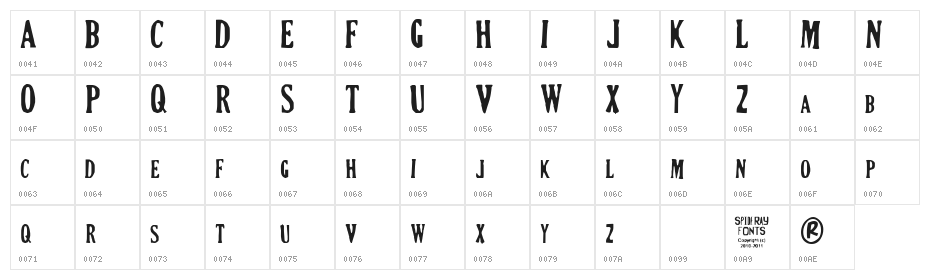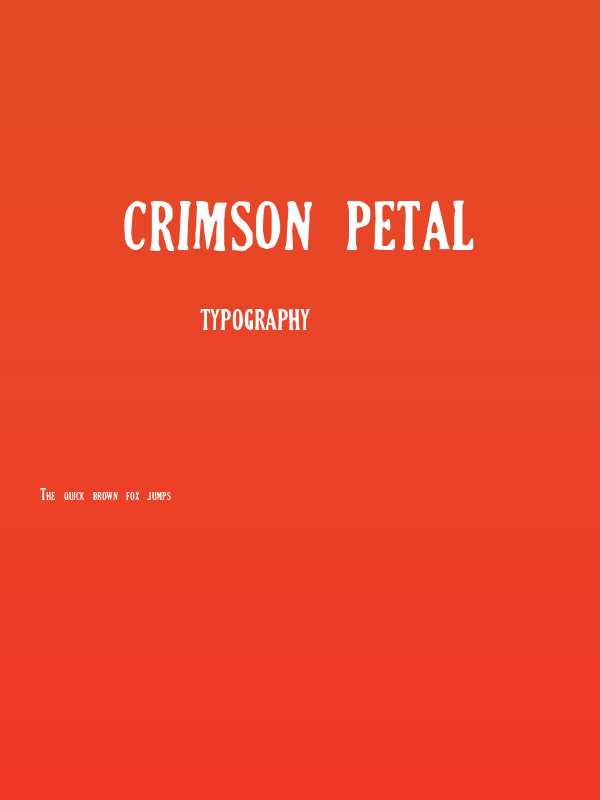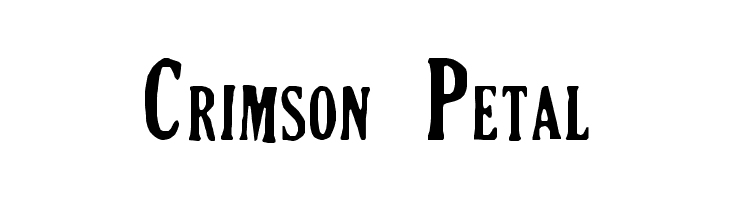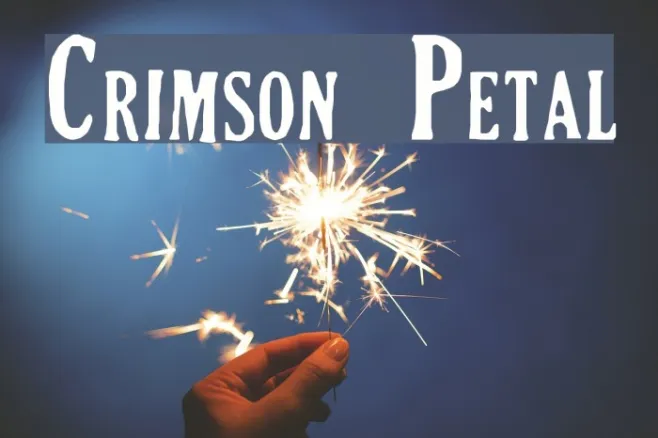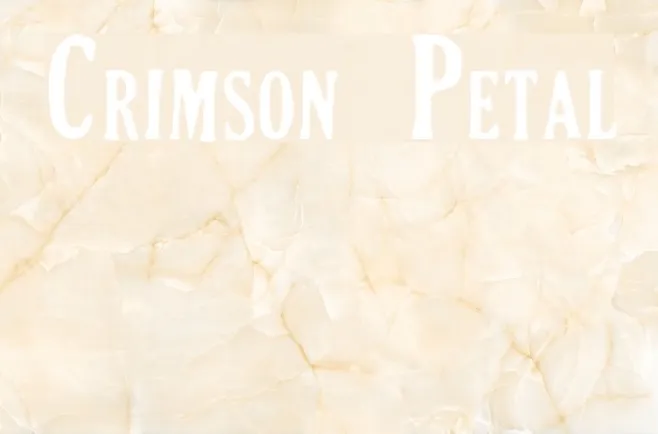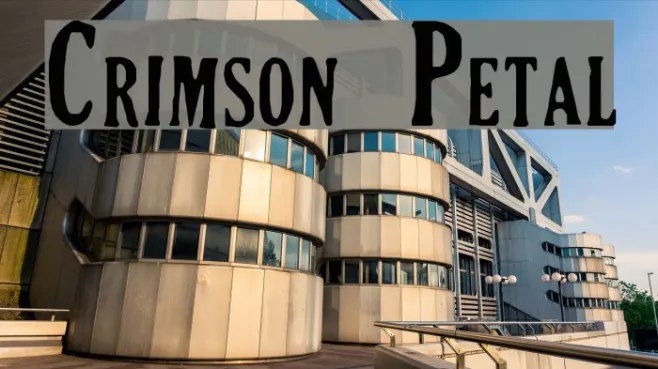
Crimson Petal Font
✎ Retro
| Cas d'utilisation | Headlines, Posters, Branding |
| Projets proposés | Ideal for vintage-themed posters, branding, and headlines that require a bold statement. |